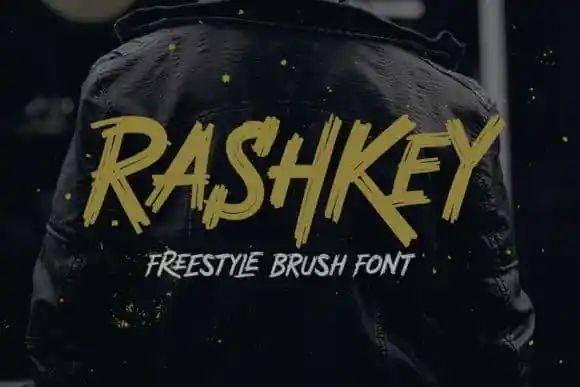
Rashkey Brush Font é uma elegante escolha para quem busca uma fonte script curvilínea e cheia de textura. Feito pelo designer Arterfak, essa fonte tem um estilo natural que se adequa perfeitamente a projetos criativos como marcadores de água na fotografia, capas de álbum, logos ou cartões de visita. Suas linhas são levementes mas detalhadas e dinâmicas, o que as torna ideais para criar design sofisticado e único. Seja você um artista digital, designer gráfico ou simplesmente um amante da arte visual, essa fonte oferece uma maneira única de dar vida aos seus projetos. Com sua variedade de aplicações, Rashkey Brush Font está sempre pronta para moldar a forma em que você veio desenhar seu próximo design.